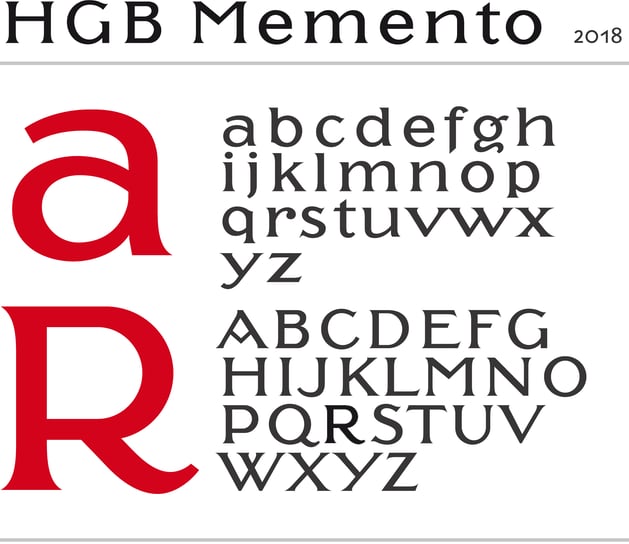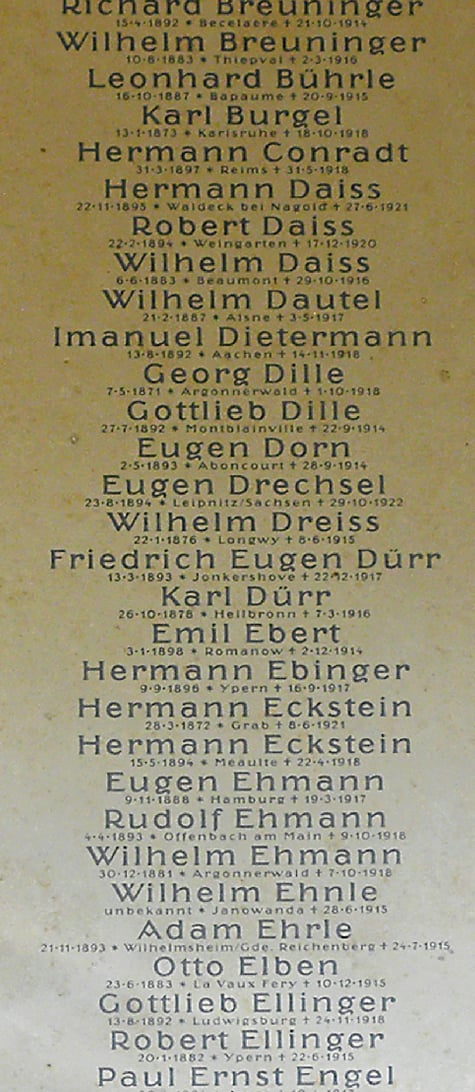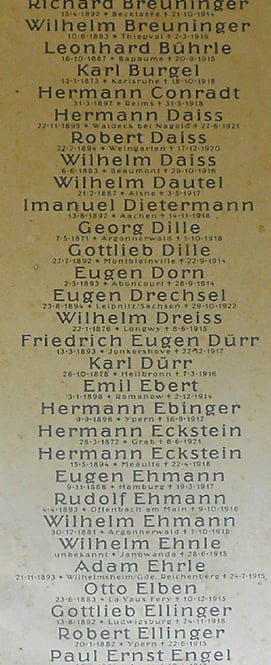
HGB Memento
1925 wurden auf dem Backnanger Stadtfriedhof 12 Bronzetafeln angebracht mit den Namen der im Ersten Weltkrieg gefallenen Backnanger. Diese Tafeln wurden 2016 aus den Verankerungen gerissen und gestohlen. Glücklicherweise hatte Dr. Roland Idler vom Volksbund Kriegsgräberfürsorge alle Tafeln erst vor wenigen Jahren fotografiert. Die reliefartige Beschriftung der Bronze-Tafeln war offensichtlich manuell modelliert, weil die Form einzelner Buchstaben deutlich variierte. Die Schrift hatte, wie auch die Architektur der Gedächtnishalle, noch starke Jugendstil-Anklänge. Ihre Proportionen waren sehr eigenwillig mit extrem kurzen Ober- und Unterlängen, um sehr enge Zeilenabstände zu ermöglichen. Diese Schrift wollte ich für die neuen Tafeln unbedingt erhalten und so entstand ein digitaler Font, mit dem die neuen Tafeln gesetzt und per Sandstrahl in Stein graviert werden konnten. Seit 2023 ist die Memento über HGB-fonts bei myFonts verfügbar.